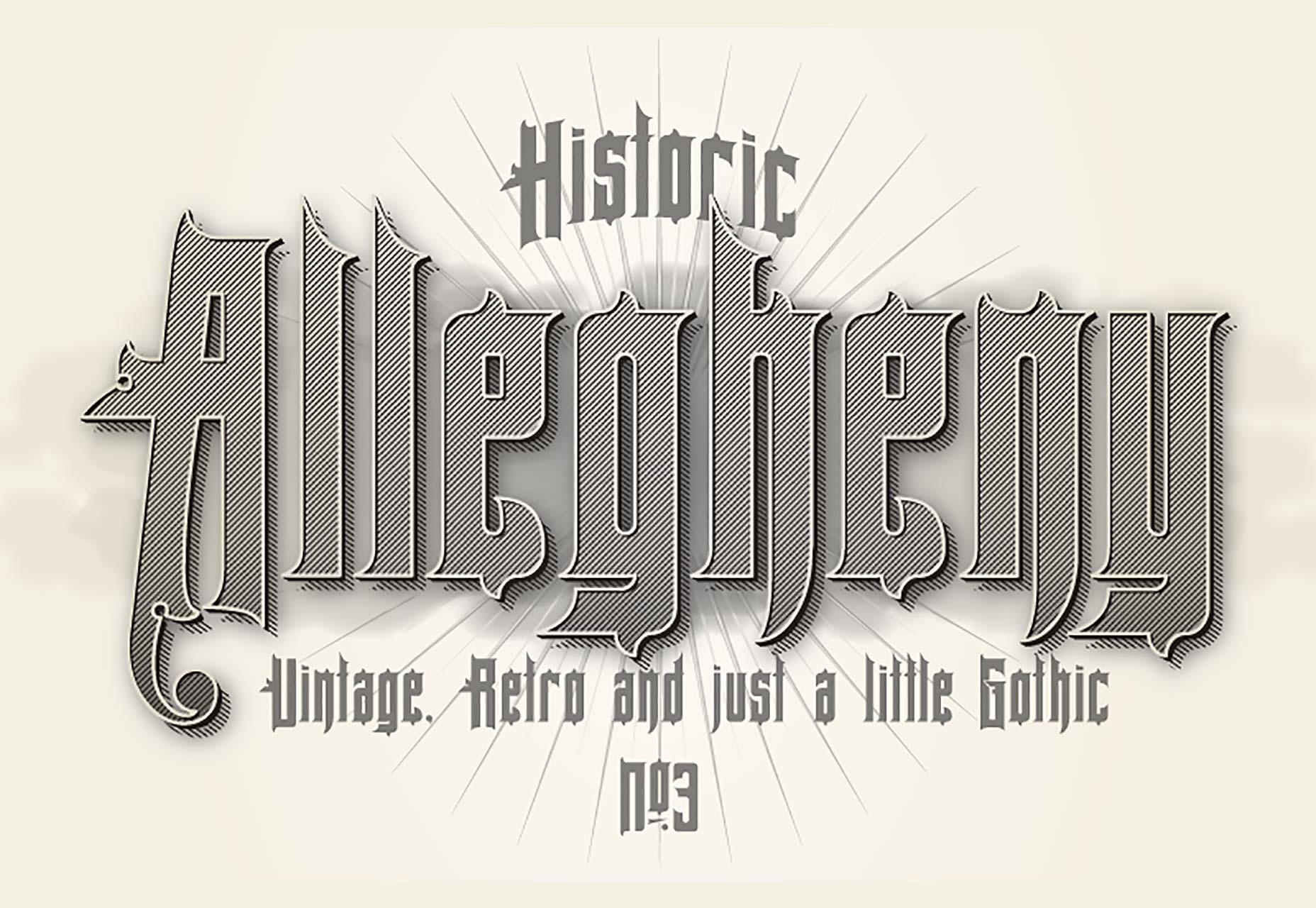
Font del giorno: Allegheny PA
il font che vi presentiamo oggi é: Allegheny PA
un font dai chiari tratti del 1900 di gusto vintage o retrò che dir e si voglia e con glifi gotici.